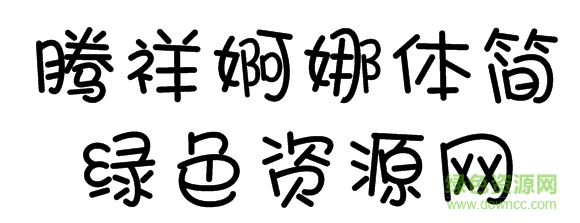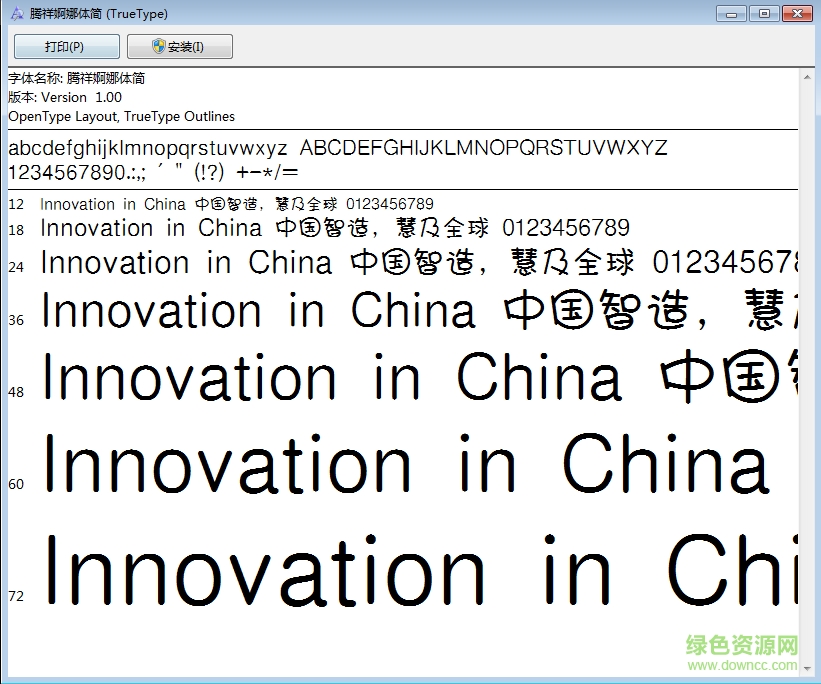
騰祥婀娜體簡(jiǎn)是一款有著美好造型和姿態(tài)的騰祥字體,婀娜多姿如少女的邢臺(tái),童趣橫生給人舒適視覺(jué),綠色資源網(wǎng)歡迎大家免費(fèi)下載!
字體為POP手繪字體,是由設(shè)計(jì)師孔淼手繪完成每個(gè)字形的原稿,再由騰祥公司調(diào)整修改完成的美術(shù)體字庫(kù)。整幅字風(fēng)格統(tǒng)一、行文規(guī)整,字里行間充滿(mǎn)童真稚趣,彰顯活潑靈動(dòng)的個(gè)性。筆畫(huà)圓柔、舒緩隨行、形同婀娜。
騰祥婀娜體有著童真童趣的特色,編碼為GB2312-80,為騰祥字庫(kù)今年全新推出的版本,有卡通字體和手寫(xiě)體的特色,為你的字庫(kù)增加一種新的風(fēng)景!